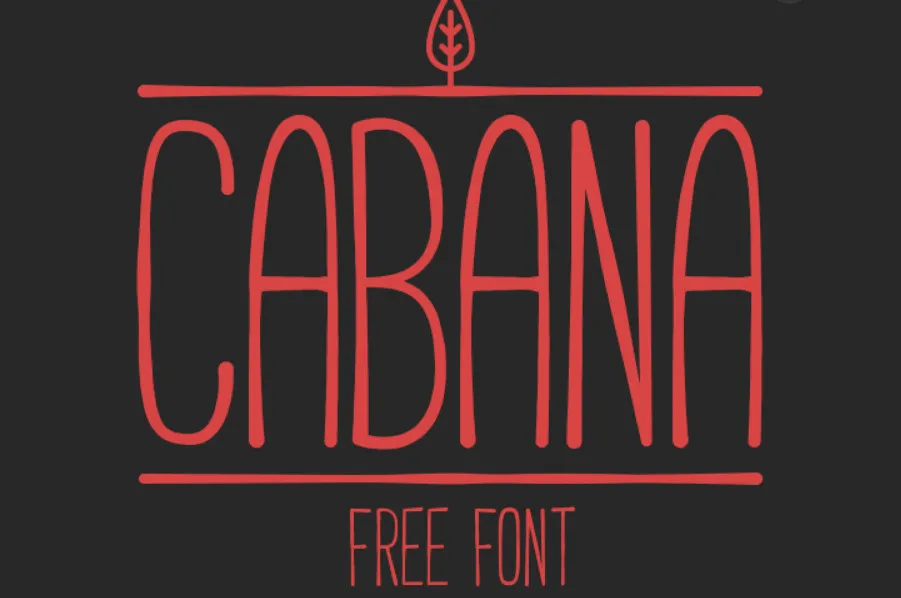
CABANA Typeface – Fonte Grátis
CABANA Typeface
CABANA Typeface é uma tipografia bold e moderna criada pelo designer francês Adrien Coquet a partir de Lille, na França. Inspirado no movimento desenho do design gráfico internacional contemporâneo, CABANA oferece uma paleta vibrante e poderosa que se destaca em qualquer projeto visual. Esta fonte é perfeita para logos, cabeçalhos, títulos de página e impressões digitais. Seu design elegante cria um impacto imediato, tornando-o a escolha perfeita para qualquer tipo de trabalho criativo. CABANA oferece uma experiência de uso excepcionalmente fluida que combina os benefícios do tipo chamativo com a simplicidade e modernidade necessárias para projetos profissionais exigentes. Seja você um designer gráfico, uma marca ou uma editora digital, CABANA é o atalho perfeito para criar resultados extraordinários em sua próxima peça de design.